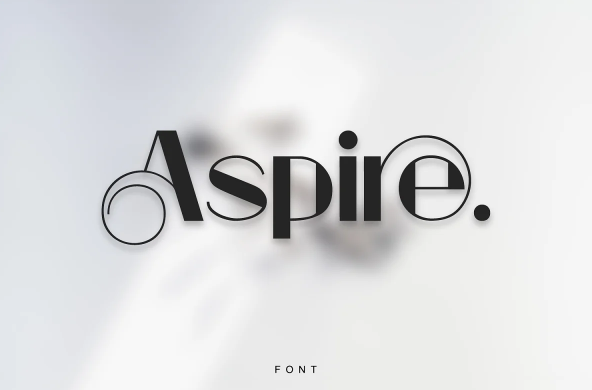
Aspire - уникальный и современный дисплейный шрифт, идеально подходящий для заголовков, крупного текста, брендинга, логотипов и использования на дисплеях. Этот шрифт может стать отличным выбором для создания выдающихся логотипов, рекламного контента и маркетинговой графики, способных привнести уникальность и свежесть на самом высоком уровне.
Шрифт идеально подходит для создания уникальных монограмм, логотипов и айдентики с помощью этих комбинаций. Пожалуйста, посмотрите примеры, показанные выше, чтобы получить представление о возможностях этого шрифта.
Aspire поставляется с расширенным набором латинских символов и лигатур, всего 220 глифов.